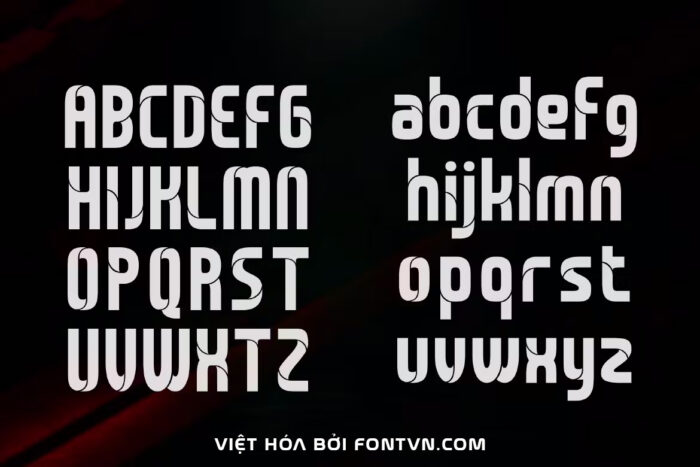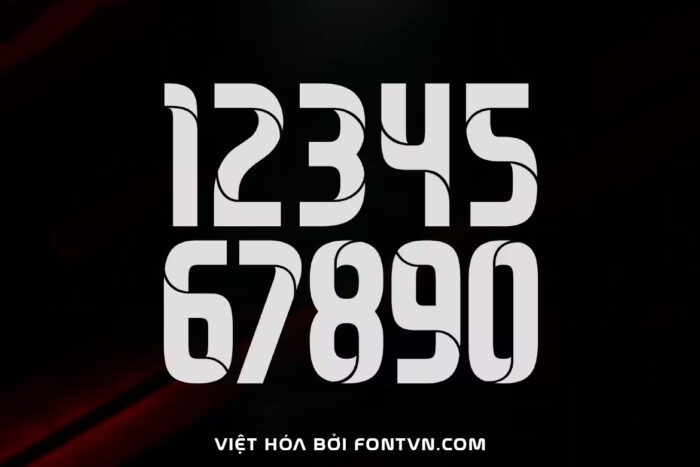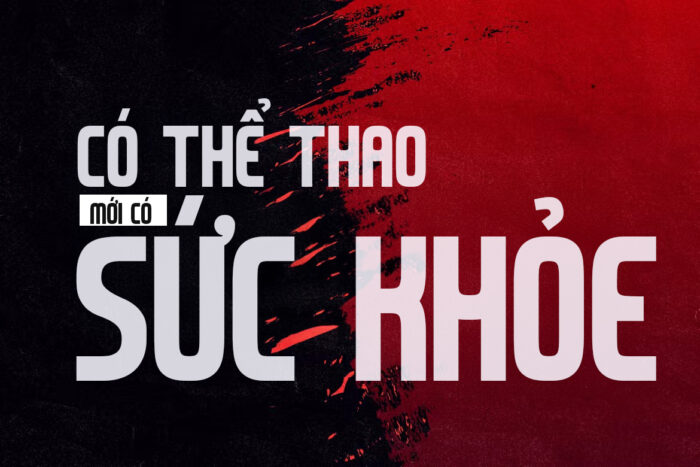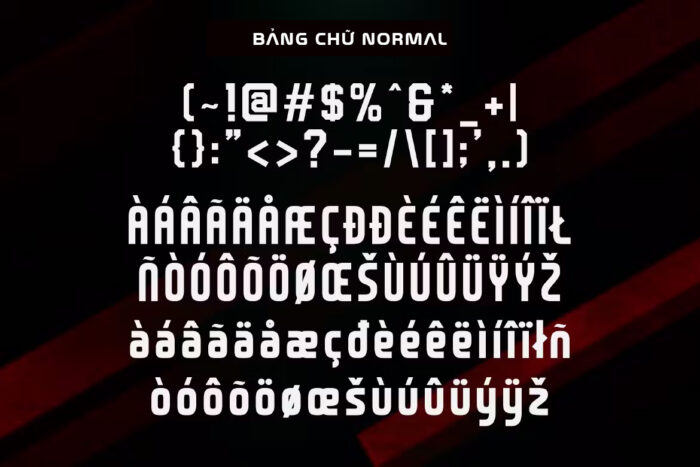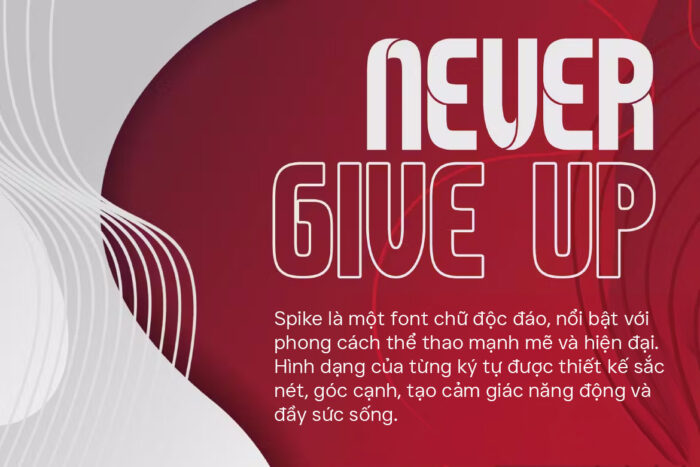
DVN Spike Việt hóa – Font chữ mang đến tinh thần thể Thao Hiện Đại Trong Thiết Kế
Spike là một font chữ độc đáo, nổi bật với phong cách thể thao mạnh mẽ và hiện đại. Hình dạng của từng ký tự được thiết kế sắc nét, góc cạnh, tạo cảm giác năng động và đầy sức sống. Các đường nét tinh tế và mạnh mẽ kết hợp hài hòa, mang lại sự cân đối và ấn tượng thị giác mạnh mẽ. Phong cách chữ của Spike đặc biệt phù hợp cho các dự án liên quan đến thể thao như logo đội bóng, poster sự kiện thể thao, áo đấu và banner quảng cáo. Ngoài ra, Spike còn có thể ứng dụng trong thiết kế các sản phẩm giải trí như bìa truyện tranh, game hoặc phim hành động, tạo nên sự cuốn hút và chuyên nghiệp. Với Spike, bất kỳ thiết kế nào cũng sẽ trở nên nổi bật và đầy phong cách.
Font này có 2 phong cách bình thường và kiểu chữ được cắt nét cách tân.